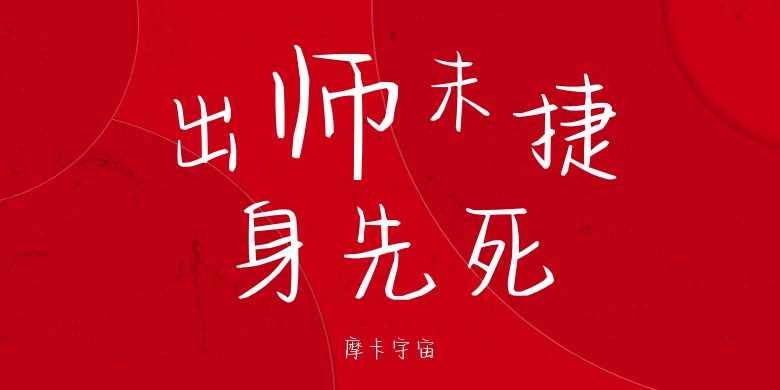
摩卡宇宙
摩卡宇宙,这款字体结构工整、笔画清晰,兼顾美观与易读性,适用于标题、正文、海报、包装、LOGO 等多种场景。字形优雅稳定,风格百搭耐看,适配日常排版与创意设计,让文字呈现更舒适、更具质感。摩卡宇宙一笔一画,皆是细节,以均衡的比例、流畅的线条打造舒适视觉体验,字形端正大气,风格简约现代。无论是商业设计、品牌宣传还是日常排版,都能轻松驾驭,让文字更有格调与力量。摩卡宇宙字体下载。